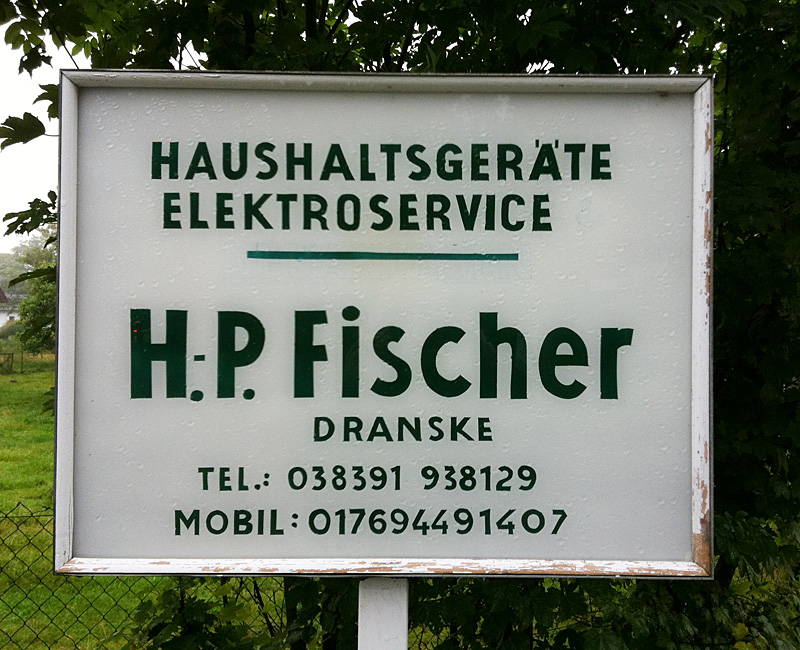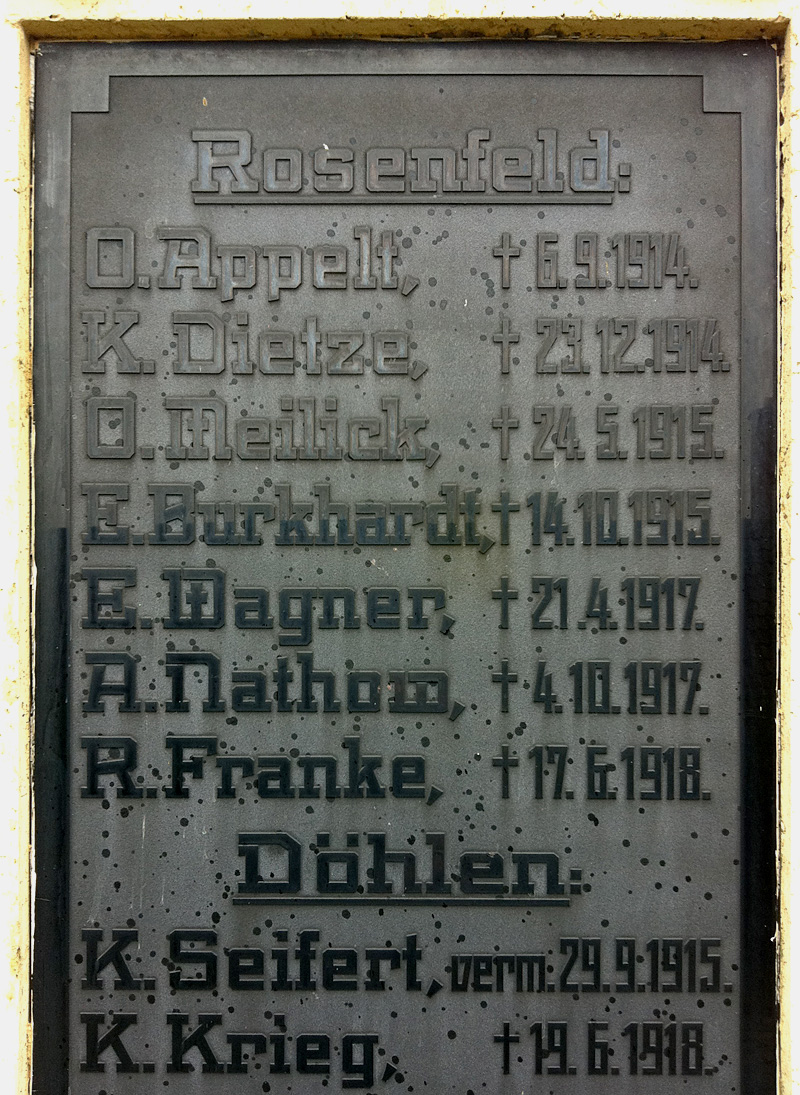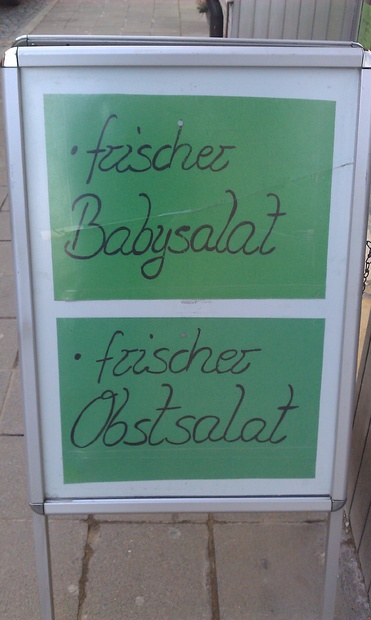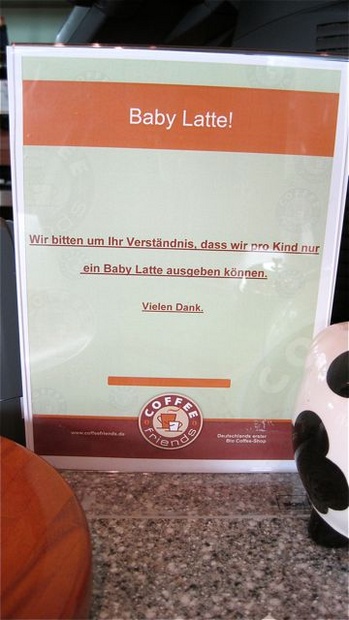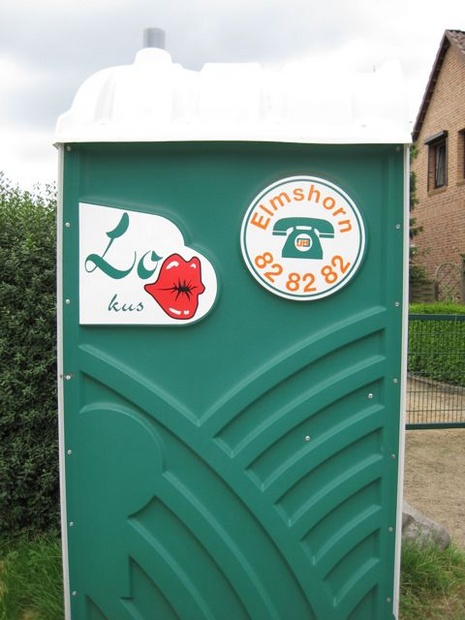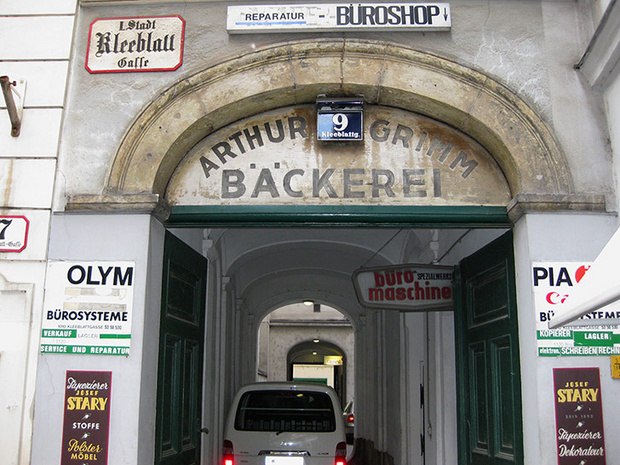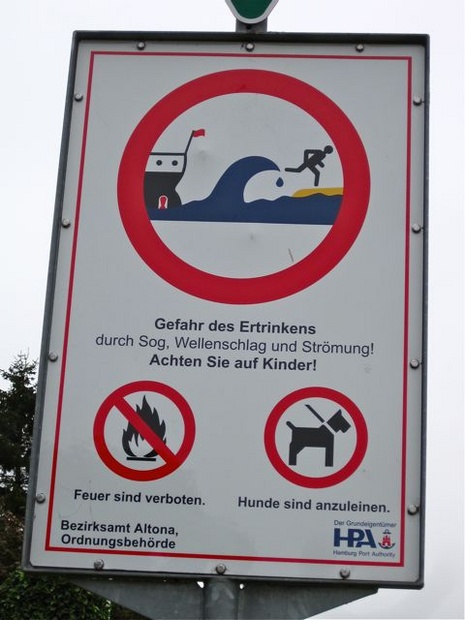
Für Euch in Bayern aufgelesen und sorgsam in meiner kleinen Typophiliertrommel nach Hause getragen …
ei ei ei, sind das nun gespitzte Lippen oder ist das eine hämorrhoidale Rosette?
In Wien gibts viel zu entdecken, auch unglaublich viele typografische Schmankerl. in dieser Hofeinfahrt prallen gleich mehrere Stilepochen aufeinander.
Sieht aber irgendwie gewollt aus … muss ein sehr spezieller Humor sein.
Dazu passt eines von Ralfs Werken … (das ich hiermit ausdrücklich nicht despektierlich behandeln möchte, ich konnte aber den Wortwitz nicht auslassen)
die bayern haben eh ein komisches verhältniss zu babys.
die bayern haben eh ein komisches verhältnis zu babys.
Meine Güte! Was für eine Bastelarbeit beim oberen Bild … :-o
Bastelarbeit? Schaut eher nach semiprofessioneller Malerarbeit aus.
Meine Güte! Was für eine Bastelarbeit beim oberen Bild … :-o
Ja, aber ich kann mir gerade nicht helfen: irgendwie finde ich das knuffig! :-P
Bastelarbeit? Schaut eher nach semiprofessioneller Malerarbeit aus.
Nee, das sind doch ausgeschnittene Buchstaben, oder? Das sieht mir nicht gemalt aus …
… knuffig! :-P
Ja, das Wort trifft es einigermaßen. Das »Making of« würde mich ja brennend interessieren.
Ich finde das Schild auch spontan sympathisch. Und ja, das Making Of – das war bestimmt eine unglaubliche Bastelarbeit! :-D